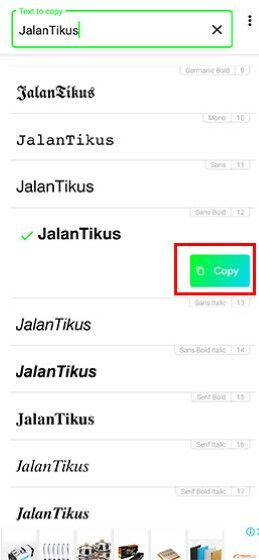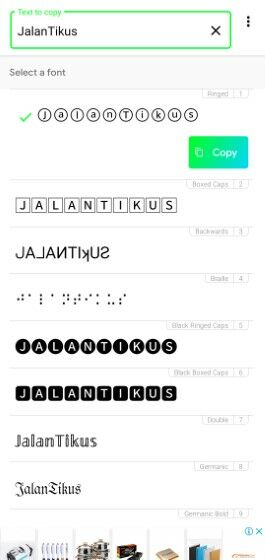
Cara mengubah font Instagram ternyata masih jarang diketahui. Padahal, ada banyak font IG unik dan menarik yang bisa kamu gunakan, loh!
Setelah belakangan tren filter Instagram aesthetic sempat booming, kini para pengguna Instagram dihebohkan kembali dengan tren font unik seperti bold atau italic.
Bahkan, style tulisan ini juga sudah sering digunakan oleh beberapa artis dan selebgram sehingga membuat banyak orang penasaran mengenai cara pembuatannya.
Sebenarnya, untuk membuat caption, bio, maupun story di Instagram dengan style ini sangat mudah dan cepat untuk dilakukan.
Nah, buat kamu yang penasaran, di artikel kali ini Jaka bakal kasih tahu cara mengubah font IG untuk bio, caption, hingga story. Cek, yuk!
Cara Mengganti Font Instagram
Untuk membuat caption foto terlihat lebih menarik dan aesthetic, ikuti saja cara ubah font Instagram dengan tulisan tebal atau tulisan miring di IG.
Untuk membuat tulisan aesthetic di IG, ada dua cara yang bisa kamu lakukan, yaitu menggunakan bantuan aplikasi pihak ketiga ataupun tanpa aplikasi.
Biar nggak makin penasaran, mending langsung aja ikuti setiap tutorial yang Jaka jelaskan di bawah ini. Dijamin IG-mu bakal makin ciamik!
Cara Mengubah Font di Instagram dengan Aplikasi
Pertama, Jaka akan menjelaskan terlebih dahulu mengenai cara membuat tulisan miring di caption Instagram dengan menggunakan bantuan aplikasi.
Selain tulisan miring, ada juga style lainnya seperti bold yang bisa kamu gunakan juga di bio maupun Instastory, geng.
Nah, untuk mengetahui cara selengkapnya, kamu bisa langsung ikuti langkah-langkah dari Jaka berikut ini.
2. Tulis kata yang ingin diubah style-nya
Langkah selanjutnya, tuliskan kata-kata yang ingin kamu ubah jenis style font-nya.
Maka hasilnya akan langsung muncul di bagian bawahnya, geng. Di tahap ini pilih style font yang ingin kamu gunakan.
3. Salin atau copy tulisan
- Jika sudah memilih jenis font yang akan digunakan, selanjutnya pilih font tersebut dan tekan tombol Copy.
Nggak hanya style font bold atau italic, tapi ada juga jenis font keren lainnya yang bisa kamu gunakan.
Selain itu, buat kamu yang juga mencari cara mengganti font di Instagram Story atau bio, kamu juga bisa ikuti langkah-langkah di atas.
Caranya juga mudah, setelah menyalin tulisan IG keren dari aplikasi text generator tadi, kamu bisa langsung menempelnya di bio ataupun story IG milikmu.
Pastinya, cara ini bisa kamu gunakan untuk mempercantik bio Instagram dan untuk membuat caption di Instagram story, lho!
Cara Mengubah Font di Instagram Tanpa Aplikasi
Jika tadi Jaka menjelaskan cara membuat tulisan bold, miring, dan style font lainnya untuk caption Instagram menggunakan aplikasi, kali ini kamu nggak perlu menginstall aplikasi apa pun.
Untuk cara mengubah font Instagram tanpa aplikasi, kamu bisa ikuti langkah-langkah dari Jaka berikut ini, geng.
1. Kunjungi situs text generator
Pertama, kamu kunjungi terlebih dulu salah satu situs text generator yang bisa mengubah font di IG sesuai dengan yang diinginkan.
Di sini, Jaka merekomendasikan untuk mengunjungi situs Instagram Fonts di URL https://igfonts.io/.
2. Tulis kata yang ingin diubah
Setelah itu, kamu tulis kata-kata yang ingin diubah style font-nya menjadi tebal, miring, atau lainnya di kolom yang sudah disediakan.
Jika sudah, maka hasilnya akan langsung muncul di bagian bawahnya, geng. Di tahap ini, kamu bisa cari style font sesuai selera.
Mulai dari tulisan tebal, miring, sambung, hingga tulisan bergaris tengah di Instagram bisa kamu temukan di sini. Lengkap, kan?
3. Salin dan copy font yang diinginkan
- Selanjutnya, copy font tulisan yang diinginkan dengan cara sentuh dan tahan pada bagian tulisan, lalu pilih tombol Copy.
4. Buka aplikasi Instagram
Selanjutnya, buka aplikasi Instagram dan buat postingan feed terbaru.
Di tahapan menulis caption, tempel atau paste tulisan tadi dengan cara sentuh dan tahan hingga muncul tombol Paste. Bakal makin keren kalau pakai caption Bahasa Inggris!
- Setelah itu, pilih tombol Share untuk membagikan postingan ke feed. Selesai, deh.
Gampang, kan, cara membuat tulisan aesthetic di Instagram tanpa aplikasi tadi? Selain untuk caption, langkah-langkah tadi juga bisa kamu ikuti untuk cara mengubah font di bio Instagram tanpa aplikasi.
Akhir Kata
Nah, itulah tadi cara mengubah font Instagram yang bisa kamu lakukan untuk membuat tulisan aesthetic pada caption, bio, hingga story Instagram.
Kamu juga bisa menggabungkannya dengan beberapa jenis font lain agar postingan lebih terlihat menarik dan berbeda dengan yang lain.